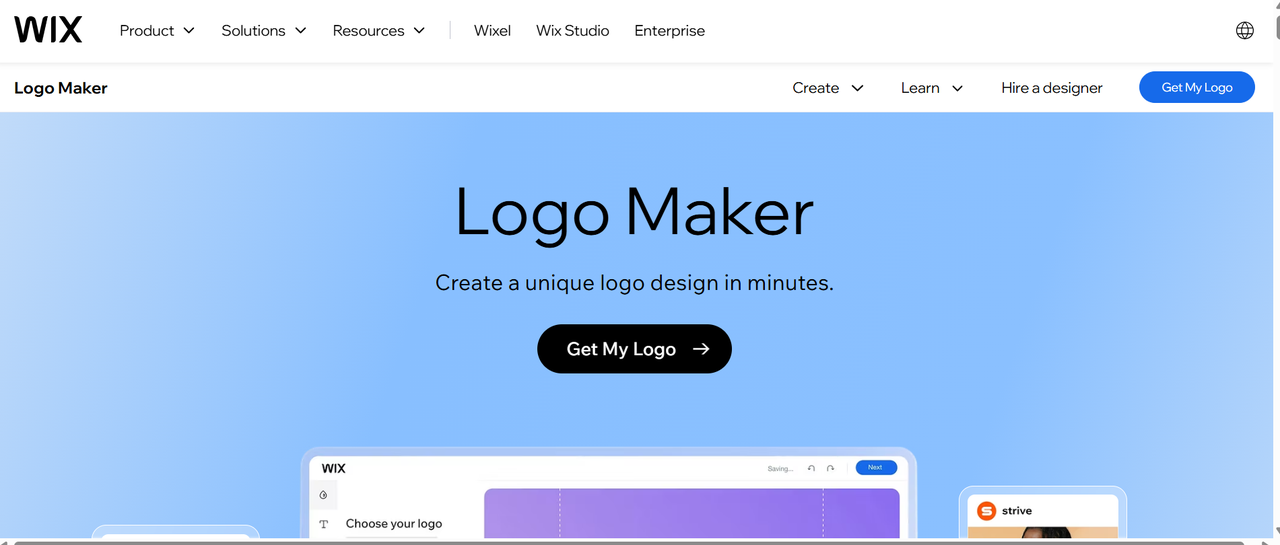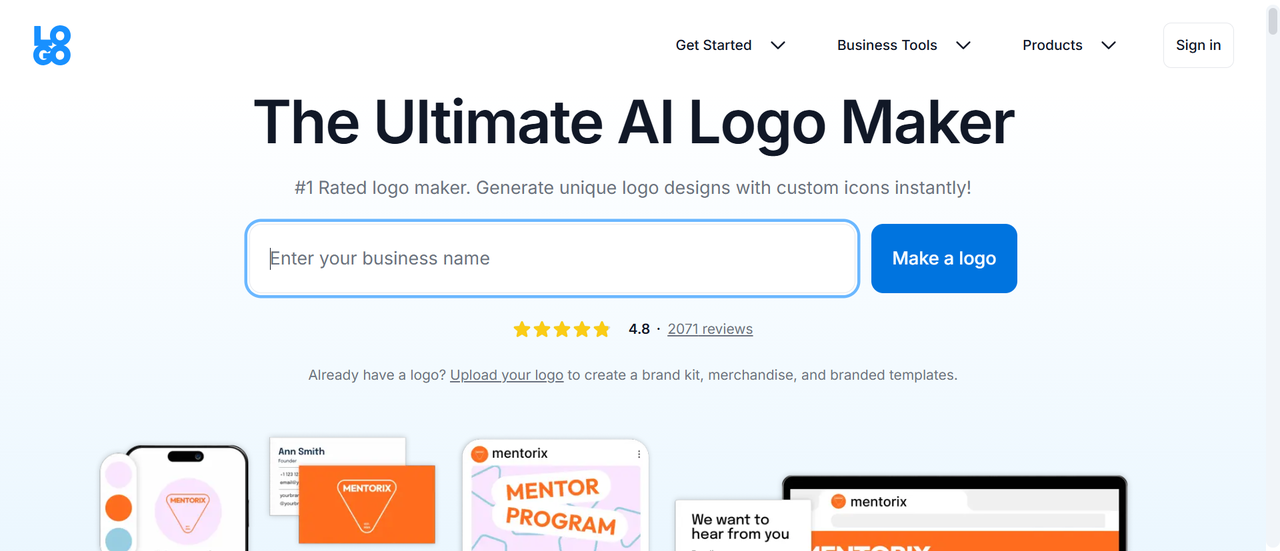
Logo字体免费设计网站推荐!100%干货分享
支持 Logo 字体免费设计的网站推荐,别再为 Logo 设计头疼啦!本文为你推荐 3 款更好用的免费 Logo 生成器,它们分别是字由,Wix logo maker 和 Logo.com,这 3 个网站均支持免费 Logo 设计,并且操作流程也十分简洁,新手小白初次操作也不会太困难。接下来,本文将为大家分别讲解这 3 个网站,一起来 Get 更简洁,更优质的 Logo 字体设计效果吧!
1、Logo 字体在线设计,前往【字由】更省心
之前在字由中做 Logo 设计,可能只能使用站内提供的字体素材,现在字由上线了一款新的 “AI 工具”,可以打造自己的 AI 字体,不仅字体效果真实,还包括多种字体风格,比如发光字,镭射字,毛笔字,可爱风等等,常用的字体风格都支持一键生成,让 Logo 设计更简单,质量更高。
访问字由官网之后,在官网导航栏的【字体工具】版块即可进入 “AI 字体” 页面,在页面中可以看到官网已经给出了种类繁多的字体卡片,只需点击卡片上的 “做同款” 按钮,即可前往 Logo 字体设计界面。
在输入框输入想生成的 Logo 内容,为了保证 Logo 的设计效果,输入的内容字符数最好与字体卡片中的字符数保持一致,之后再点击 “直接生成” 按钮,等待 25 秒钟左右,一个属于自己的 Logo 字体就设计好了。更丰富的 Logo 设计效果,更简单的 Logo 的设计过程,欢迎前往【字由】体验。
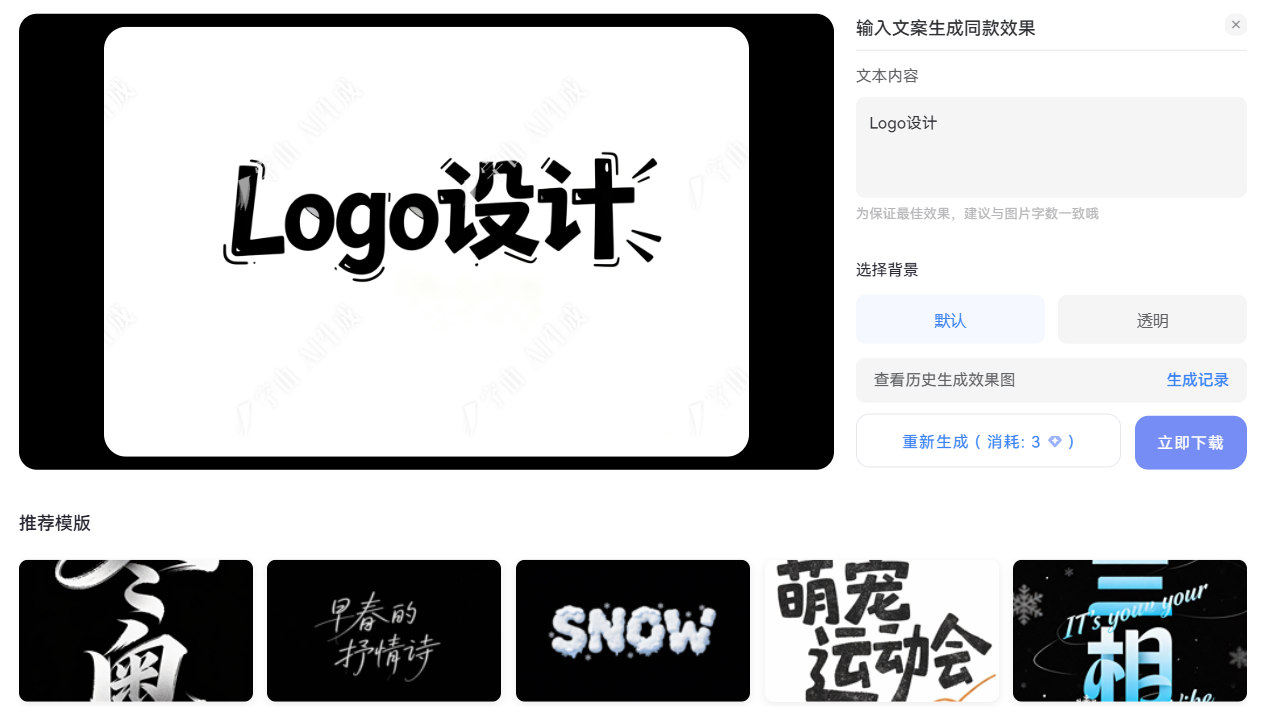
2、Wix logo maker:线上 Logo 字体设计,支持矢量图下载
Wix logo maker 除了面向字体设计师之外,更多地面向于个人品牌或者小型企业。访问 Wix logo maker 后,我们可以使用两种方法来完成 Logo 设计,一种是逐步回答问题,自己完成 Logo 设计,另一种是配合 Wix 的设计师一起来完成 Logo 设计。
前者更多地是面向于小型商家,要求回答一些商家相关的问题,比如您是什么类型的商家,想要设计什么样的 Logo 风格?更喜欢使用哪种字体等等,之后 Wix logo maker 就能参考您输入的答案来生成 Logo 设计。生成时间不会太长,如果对 Logo 的生成效果不满意,同样可以继续手动调整,比如改变 Logo 的颜色,字体,布局等等,通过这些精细调整,让 Logo 设计效果更符合预期。
3、Logo.com:丰富的 Logo 设计模板,支持线上预览
Logo.com 的使用步骤和字由有些相似,同样是需要先挑选 Logo 设计模板,然后根据模板来生成自己的 Logo 设计。不过除了字体之外,Logo.com 还给出一些好看的,经典的 Logo 文字排列方式,可以为你提供一些 Logo 设计上的灵感。
除此之外,Logo.com 还在站内提供了一些 Logo 样机,比如餐饮,名片,衣服,网站页面等,可以把设计好的 Logo 放入到样机中,在线即可查看 Logo 设计效果。不过 Logo.com 目前只支持全英文操作,这一点对于国内的设计师来说可能不太友好,尤其是刚接触 Logo 设计的新手小白,大家可以根据需要选择使用。